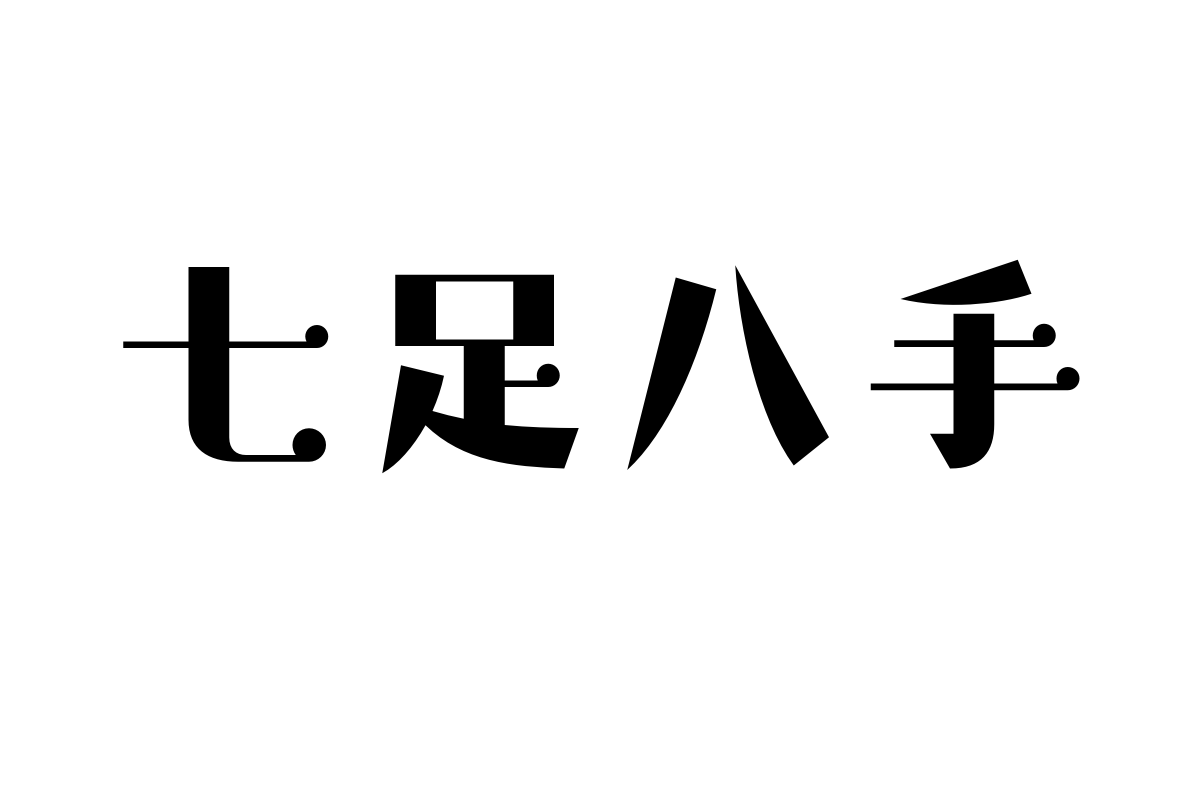
造字工房新学宋体是一款具有现代感的中文字体,它采用了简洁、清晰的设计风格,使得阅读体验更加舒适。这款字体的特点是笔画流畅,字形规整,适合用于各种需要清晰、易读的文字排版。
造字工房新学宋体的笔画粗细适中,既保留了传统宋体的特点,又加入了一些现代设计的元素,使得整体风格更加符合现代人的审美需求。此外,这款字体还具有一定的可扩展性,可以根据需要进行个性化定制。
总的来说,造字工房新学宋体是一款非常适合现代商业、办公、广告等领域使用的中文字体。